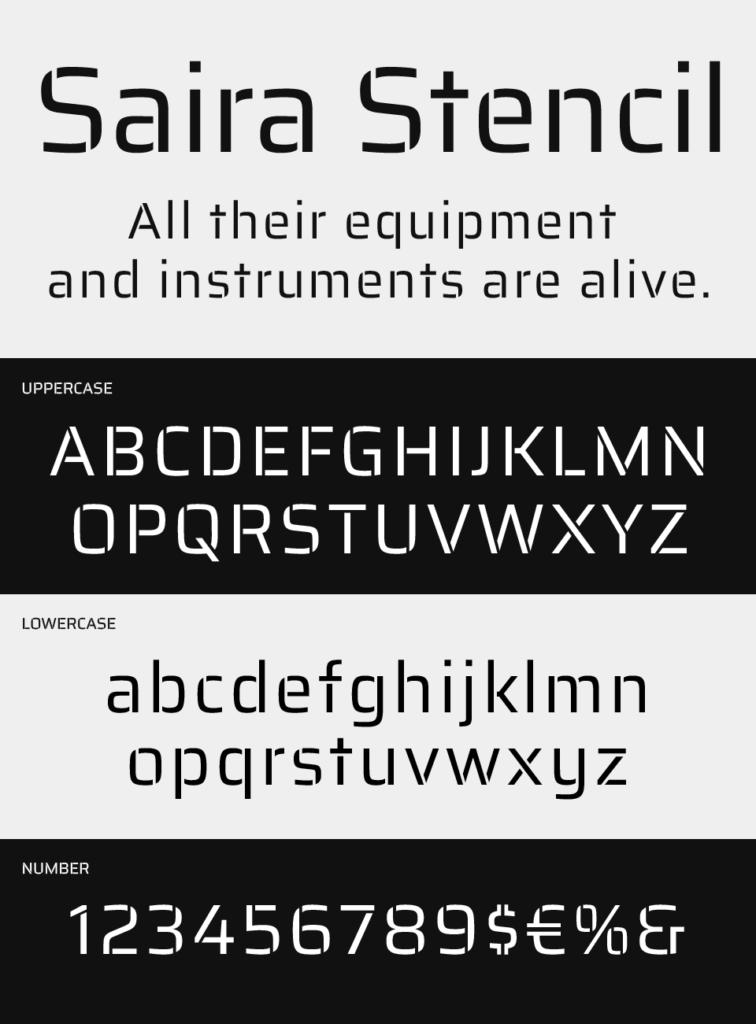
Saira Stencilフォントは、近未来的な角丸フォルムとステンシルを組み合わせた、メカニカルでスマートな印象のサンセリフフォントです。
ステンシルが装飾されていることで、シンプルなレイアウトでも強い個性があり、ほどよい親しみやすさも感じられます。サバイバル系はもちろん、テクノロジー系やゲーム系のタイトルにも映えるフォントです。